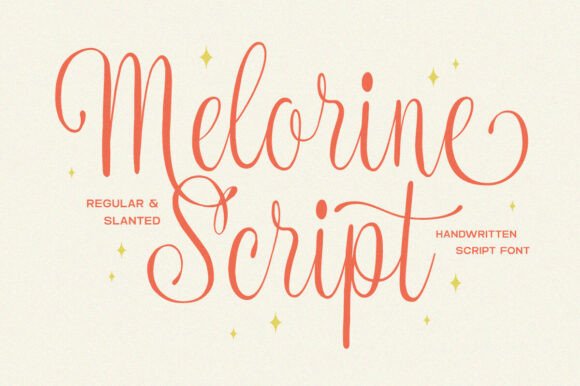
Melorinescript
Melorinescriptのような高品質の素材をお探しの場合、このプレミアムパッケージはクリエイティブなプロジェクトに素晴らしい選択です。
精密に作られたMelorinescriptは、クリーンなベクター、滑らかなタイポグラフィ、そして安心のための商用ライセンスを提供します。
POD(オンデマンド印刷)製品、結婚式の招待状、またはソーシャルメディアのグラフィックを作成している場合でも、Melorinescriptは理想的です。